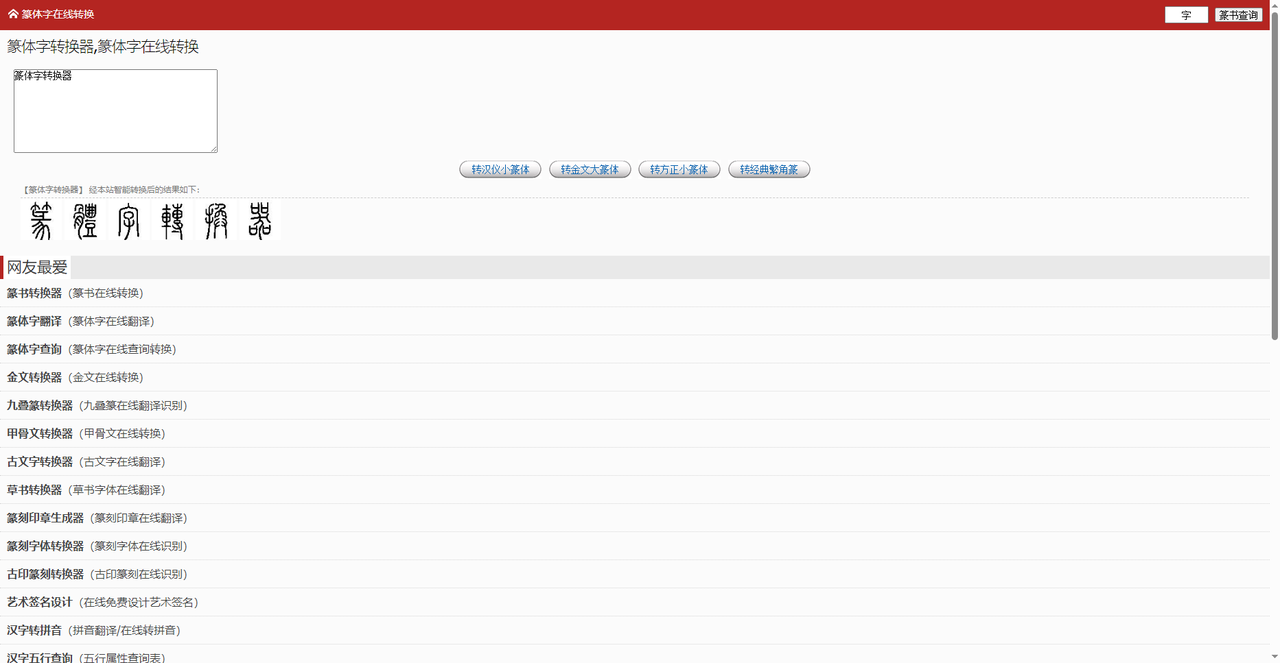
篆书字体转换器推荐:在线生成小篆、大篆等字体
篆书是中国最古老的字体,甲骨文、金文、大篆、小篆,一路演变而来。字形修长、笔画圆转、结构匀称。做印章、刻匾额、设计文创产品、做古风Logo,篆书总能拉满文化气息。但问题是,篆书在普通电脑字库里几乎没有,而且现代人大多不认识篆字,更不会写。现在不用愁了,有一批在线篆书字体转换器,你输入简体汉字,它就能自动帮你转成小篆、大篆、九叠篆等效果。今天实测了5款,有提供正版商用篆书字体的大平台,也有在线一键转换的小工具,从设计师到普通爱好者都能用。
字由作为国内领先的字体管理与AI平台,也收录了多款正版篆书字体。打开字由客户端或网页版,在搜索框输入“篆书”,或者通过筛选栏在字体类型中找到“篆书”分类,你就能看到字由整理的专业篆书字体列表。
字由提供了多款商用版权篆书字体:
- 汉仪篆书繁
- 汉仪粗篆繁
- 汉仪娃娃篆简
- 三极秦韵小篆
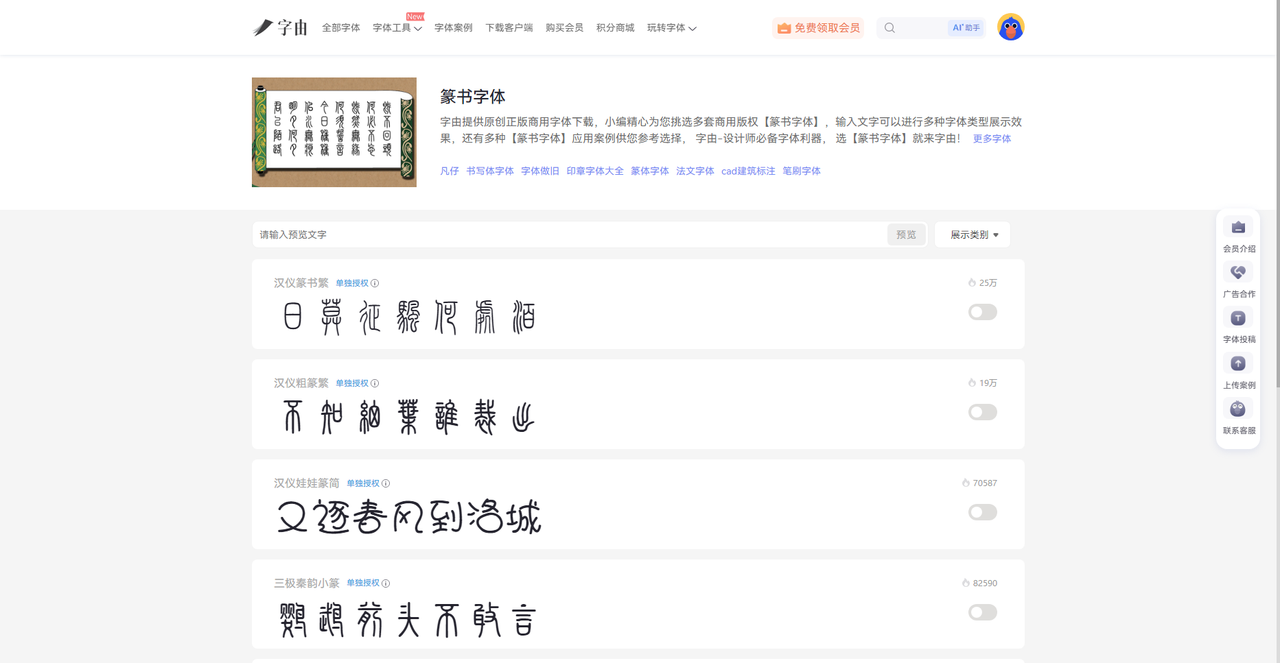
如果你是设计师,需要用篆书做品牌Logo、印章效果或产品包装,字由的操作非常方便:
- 找到你喜欢的篆书字体,例如“汉仪篆书繁”。
- 打开软件,输入文字,选择该篆书字体,即可自由排版、调大小、改颜色。
字由还提供了在线预览功能:在字体详情页输入你的文案(例如品牌名“汉风”),可以实时看到这款篆书字体的实际效果,不用购买就能判断合不合适。
2、篆体字在线转换工具
第二个网站是一个专业的篆体字在线转换工具。它提供了多种篆书类型的快速转换入口,包括:
- 转汉仪小篆体
- 转金文大篆体
- 转方正小篆体
- 转经典繁角篆
此外,还有“网友最爱”板块,包括篆书转换器、篆体字翻译、金文转换器、九叠篆转换器、甲骨文转换器、古文字转换器、草书转换器、篆刻印章生成器、篆刻字体转换器等。功能非常齐全,几乎覆盖了古文字爱好者和印章设计者所有需求。这个网站适合那些需要快速、免费转换少量文字的用户,或者对古文字有浓厚兴趣的爱好者。转换结果以图片形式存在,清晰度足够日常分享和参考。
3、字体视界
第三个网站是字体视界(旗下的“篆书字体转换器”。它提供了更丰富的调节选项,适合需要精细控制输出效果的用户。页面中央是一个大的输入框,输入需要转换的文字。下方“选择字体”下拉菜单中可以选择“三极小篆简”“汉标铁林篆(简)”“汉标铁林篆(繁)”“印品篆遇简”等篆书字体。然后你可以调节各种文字特效。设置完成后,点击“下载图片”即可获得高清篆书图片。页面还提供了“商用授权”和“免费字体大全”入口,方便有商业需求的用户购买正版授权。
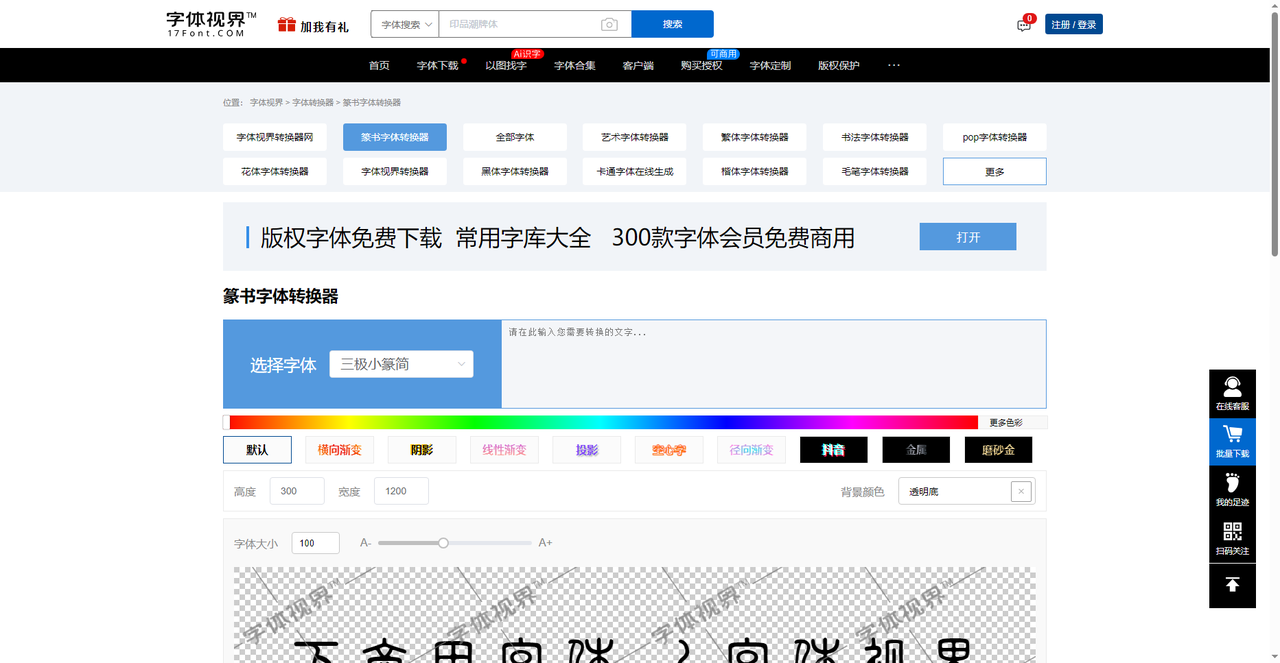
4、篆体字在线转换软件
第四个网站是一个篆体字在线转换软件。它的界面与第二个类似,提供了多种转换按钮、。除此之外,还提供了“猜你喜欢”的甲骨文转换器、金文转换器、汉字转拼音、五行查询等工具,功能繁多。该站的亮点在于它附带了详细的篆书知识科普,包括篆书的历史演变、分类(甲骨文、大篆、小篆)、基本笔画、代表作品等。对于想了解篆书文化的用户来说,这不仅是工具,也是学习的入口。使用方法同样简单:输入文字,点击对应按钮,下方展示转换结果图片。不需要注册,免费使用。它更偏向于教育和爱好用途,设计师也能用它快速生成灵感参考。
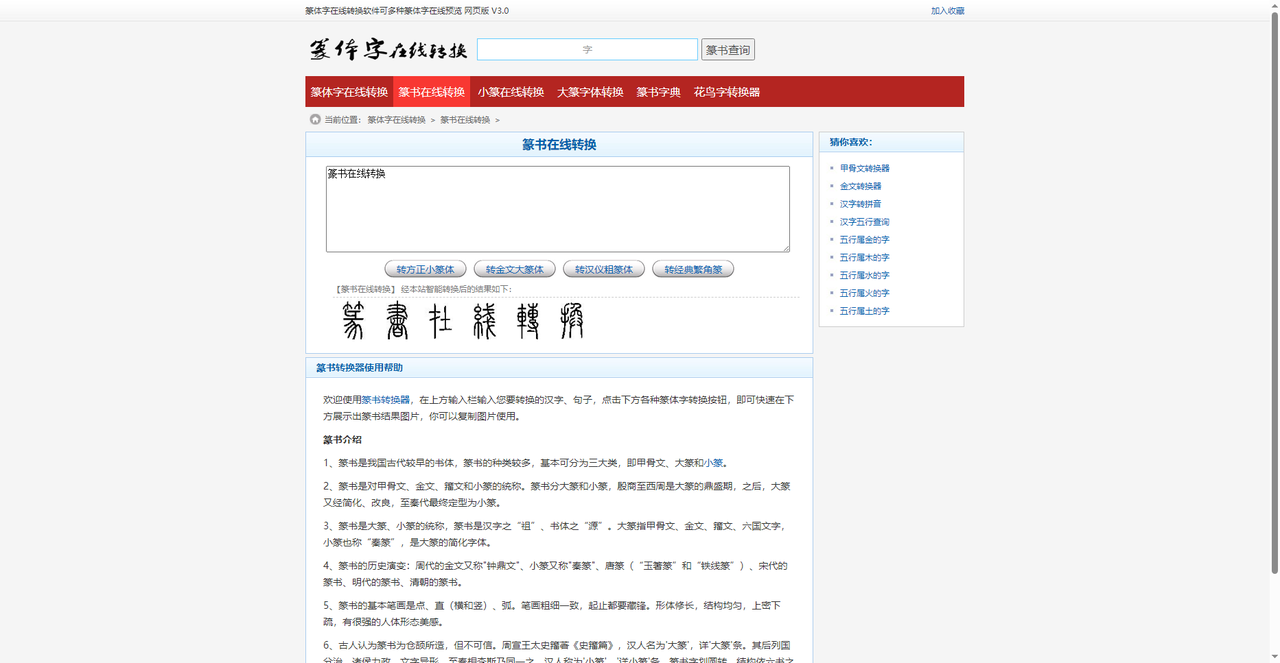
5、千千秀字
第五个网站是千千秀字的“篆体字在线转换”功能。它的特点在于提供了简体版和繁体版两种转换模式。这是因为简体字存在“多字简化为单字”的规则,例如“台”“臺”“颱”在简体下都转成“台”的小篆,繁体版则会分别对应各自字形。用户可以根据实际需要选择。操作方式:在上方输入文字(最多200个字),选择“简体版”或“繁体版”,然后点击“转换成篆书字体”,下方就会生成预览PNG图片。页面提示“在此生成的篆体字(小篆)预览为PNG图片,勿商用”,说明仅供个人学习和参考,不可用于商业项目。
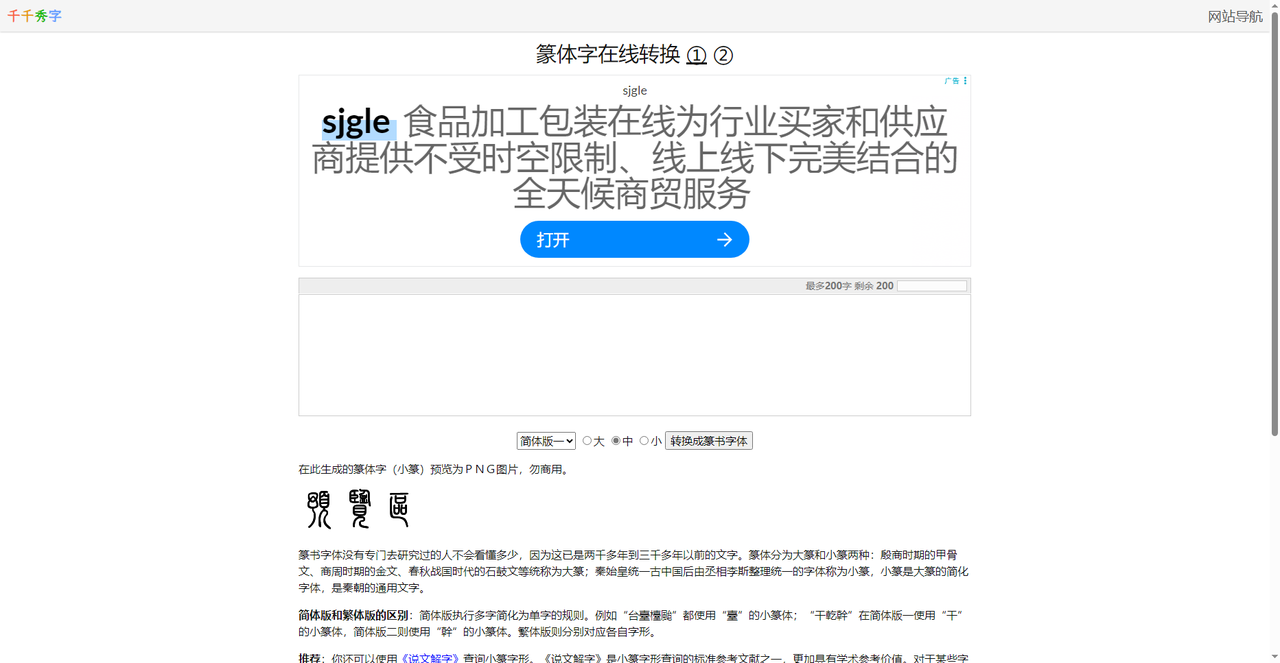
五款篆书字体转换工具,每个都非常实用。字由最适合专业设计师,提供汉仪篆书繁、汉仪粗篆繁等正版商用篆书字体,激活即可在PS、AI中使用,适合品牌VI、印章设计等对版权和品质要求高的项目;只要输入你想转换的文字,选工具,几秒钟就能看到圆转流畅、古朴典雅的篆书效果。无论是做印章、Logo,还是学习古文字,总有一款能帮你。